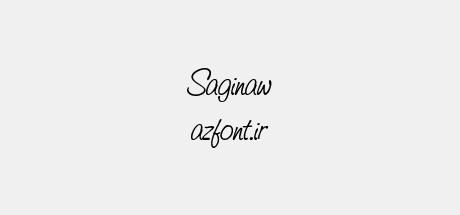
Saginaw
فونت زیبای رایگان Saginaw
قلم زیبای Saginaw Bold از سری قلم های بسیار زیبا برای تایپوگرافی و لوگو تایپ می باشد.این قلم در وزن Bold و توسط HT طراحی و منتشر شده است.